一、字体设计的标准
1.文本的易读性:
文本的关键作用是在视觉传达设计中往大家传递创作者的用意和各种各样信息内容,要做到这一目地务必考虑到文本的总体需求实际效果,给人一种清楚的视觉效果印像。因而,设计方案中的文本应防止复杂零乱,让人易认,通俗易懂,切勿以便设计方案而设计方案,忘了字体设计的压根目地是以便更强,更合理的传递创作者的用意,表述设计方案的主题风格和设想潜意识。
2.授予文本个性化:
文本的设计方案要听从于著作的艺术风格。文本的设计方案不可以和全部著作的艺术风格相摆脱,更不可以发生冲突,不然,便会毁坏文本的需求实际效果。一般说来,文本的个性化大概能够 分成下列几类:(1)庄重秀美。这一类字体样式幽美清爽,(2)格调高雅,(3)绮丽高雅。(4)牢固高挺。字体样式造型设计富有幅度,(5)简约开朗,(6)科技感强,(7)有较强的视觉效果撞击力。(8)低沉厚实。字体样式造型设计整齐,(9)具备净重感,(10)庄重雄壮,(11)不(12)可动摇。(13)轻快轻柔。字体样式生动有趣,(14)弹跳轻快,(15)节奏性和节奏性都很强,(16)给人一种生机勃勃的体会。(17)苍劲有力古色古香。这类字体样式朴素无华,(18)蕴含神韵,(19)能给人一种对远去岁月的回味无穷感受。(20)新奇与众不同。字体样式的造型设计奇特,(21)不(22)同(23)一般,(24)个性化十分突显,(25)给人的印像与众不同而(26)新奇。
3.在视觉效果应该给人一种艺术美:
在视觉传达设计的全过程中,文本做为界面的品牌形象因素之一,具备传递情感的作用,因此它务必具备视觉效果上的艺术美,可以给人一种美丽的体会。字形设计方案优良,组成恰当的文本能让人觉得开心,留有幸福的印像,进而得到优良的心理反应。相反,则让人看后内心不愉快,视觉效果上无法造成艺术美,乃至会让观众们拒而不要看,那样必然无法传递出创作者想主要表现出的用意和设想。
4.在设计方案上应富有创造力:
依据著作主题风格的规定,突显字体设计的个性化颜色,造就不同寻常的别具特色的字体样式,给人一种别出心裁的视觉效果体会,有益于创作者设计意图的主要表现。设计方案时,需从字的形状特点与组成上开展探索,持续改动,不断揣摩,那样才可以造就出颇具个性化的文本,使其外界形状和设计方案情调都能勾起大家的审美观愉快体会。
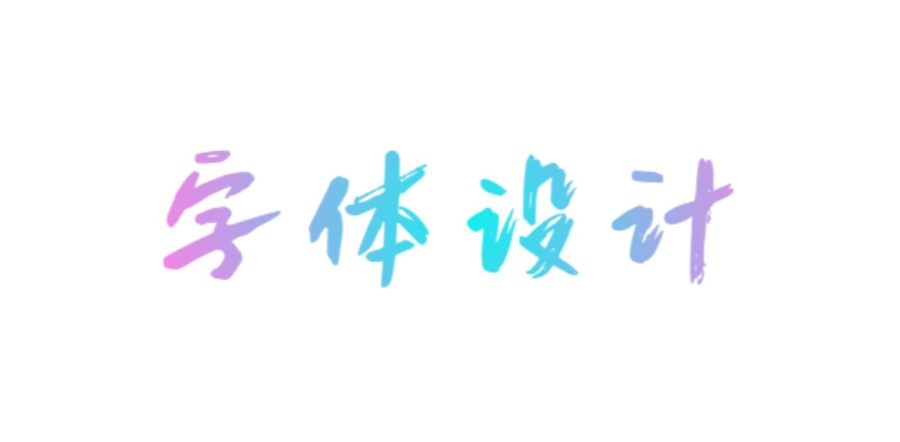
二、字体的组成
字体设计的取得成功是否,不但取决于字体样式本身的撰写,另外也取决于其应用的排列与组合是不是恰当。假如一件著作中的文本排序不善,拥堵杂乱无章,欠缺视野流动性的次序,不但会危害字体样式自身的艺术美,也不利观众们开展合理的阅读文章,则无法造成优良的视觉传达设计实际效果。要获得优良的排序实际效果,关键所在找到不一样字体样式中间的相互关系,对其不一样的对立面要素给予和睦的组成,在维持其分别的个性特点的另外,又获得总体的融洽感。以便导致栩栩如生比照的视觉冲击,能够 从设计风格、尺寸、方位、明暗交界线度等层面挑选比照的要素。但以便做到总体上组成的统一,又必须从设计风格、尺寸、方位、明暗交界线度等层面挑选融洽同样的要素。将比照与融洽的要素在听从于表述主题风格的必须下掌握分寸的应用,能导致既比照又融洽的,具备视觉效果审美观使用价值的文本组成实际效果。
字体的组成中,要留意下列好多个层面:1.大家的阅读习惯文本组成的目地,是以便提高其视觉传达设计作用,授予审美观**,诱发大家有兴趣爱好的开展阅读文章。因而在组成方法上就必须切合大家心理状态体会的次序。
下边,列举大家的一般阅读文章次序。
1.水平方向上,大家的视野一般是以从左往右流动性;竖直方位时,视野一般是从上到下流动性;超过四十五度倾斜度时,视野是以上而下的;低于四十五度时,视野是由下向上流动性的。
2.字体样式的外观设计特点不一样的字体样式具备不一样的视觉效果趋势,比如:扁体字有上下流动性的炫酷,长体字有左右流动性的觉得,斜字有往前或向斜流动性的炫酷。因而在组成时,要考虑到不一样的字体样式视觉效果趋势上的差别,而开展不一样的组成解决。例如:扁体字合适横着编辑组成,长体字合适作纵向的组成,斜体字合适作横着或趋向的排序。有效应用文本的视觉效果趋势,有益于突显设计方案的主题风格,正确引导观众们的视野按次序轻和重流动性。
3.要有一个设计方案主旋律对著作来讲,每一件著作都是有其独有的创意字体设计风格。在这个前提条件下,一个著作版块上的各种各样不一样字体样式的组成,一定要具备一种合乎全部著作设计风格的设计风格趋向,产生整体的格调和情感趋向,不可以各种各样文本开创一种设计风格,各行其是。总的主旋律应该是总体上的融洽和部分的比照,于统一当中又具备动感的转变,进而具备比照和睦的实际效果。那样,全部著作才会造成视觉效果上的艺术美,合乎大家的赏析心理状态。除开以统一文字个性的方法来做到设计方案的主旋律外,还可以从专一性上去产生文本统一的主旋律,及其颜色层面的心理状态觉得来做到统一主旋律的实际效果这些。
4.留意负空间的应用在文本组成上,负空间就是指除字体样式自身所占有的界面室内空间以外的空白页,即字符间距以及周边空白页地区。文本组成的优劣,非常大水平上在于负空间的应用是不是恰当。字的行间距应超过字符间距,不然观众们的视野无法按一定的方位和次序开展阅读文章。不一样类型文本的室内空间需作适度的集中化,并运用空白页多方面区别。以便突显不一样一部分字体样式的形状特点,需留适度的空白页,归类集中化。